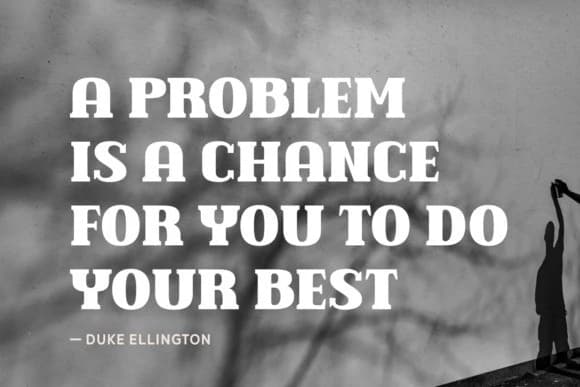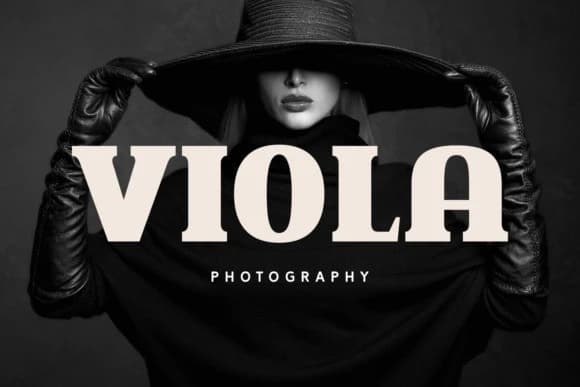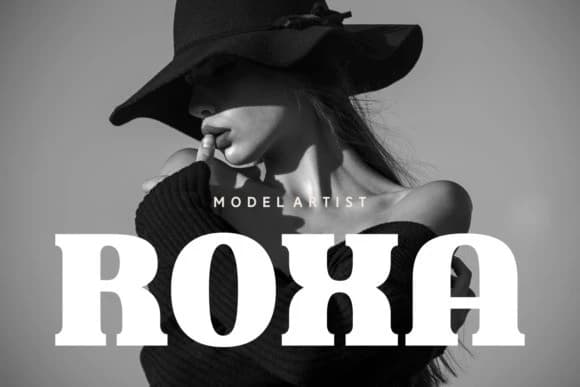
Think Alike Font
Think Alike Font, serif estetiğini zarifçe modern ve fotoğrafik tipografi estetiğiyle bir araya getirerek sanatsal bir birleşim sunar. Otantik bir hava yayıyor; çok yönlülüğü giyim ve kitap kapağı tasarımlarını sorunsuzca güçlendirirken marka kimliğine de benzersiz bir çekicilik katar.
Think Alike Font, serif, zarifçe modern ve fotoğrafik font estetiğinin sanatsal bir kaynaşmasını temsil eder. Otantikliğini yansıtır ve çok yönlülüğü belirgindir; giyim ve kitap kapağı tasarımlarını sorunsuzca geliştirirken markalara da özgün bir hava katar.